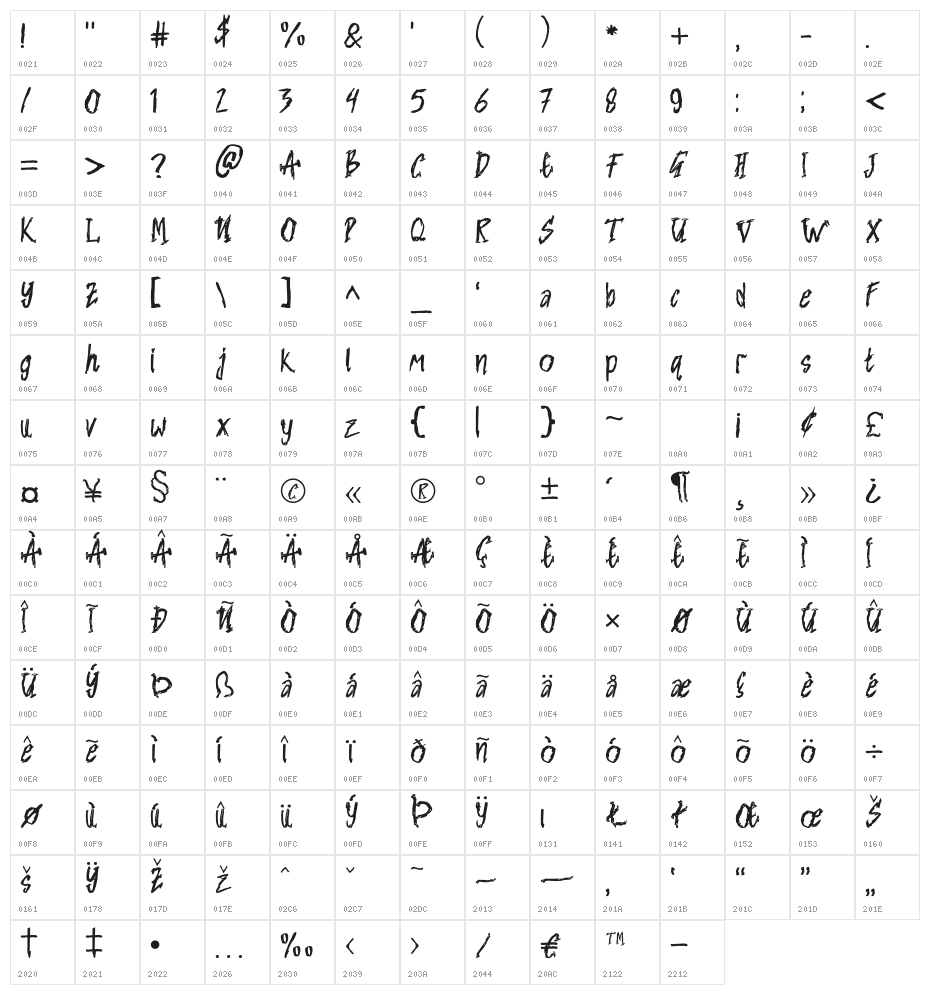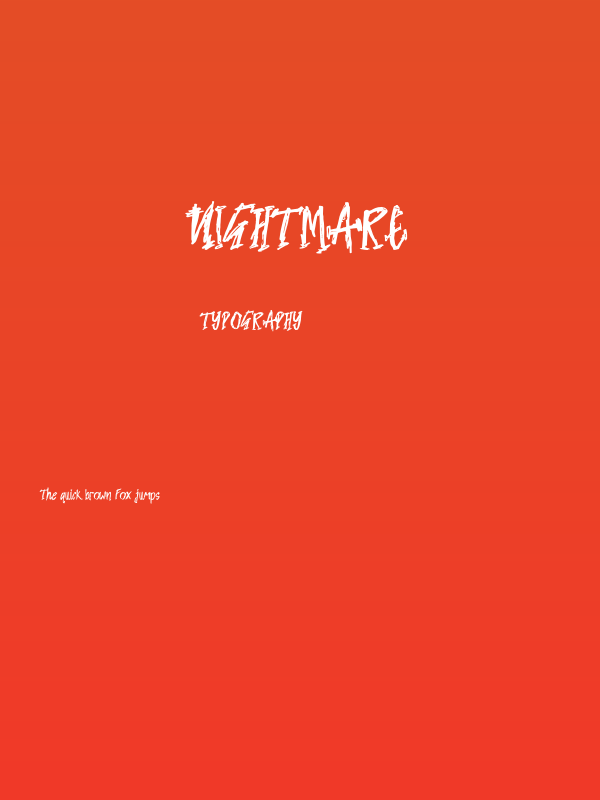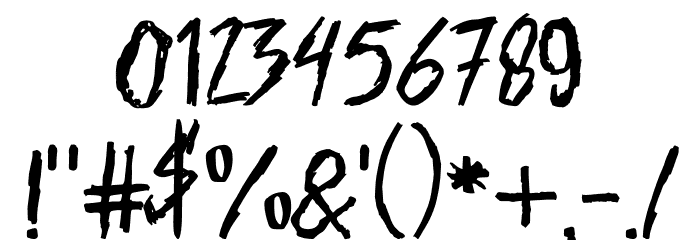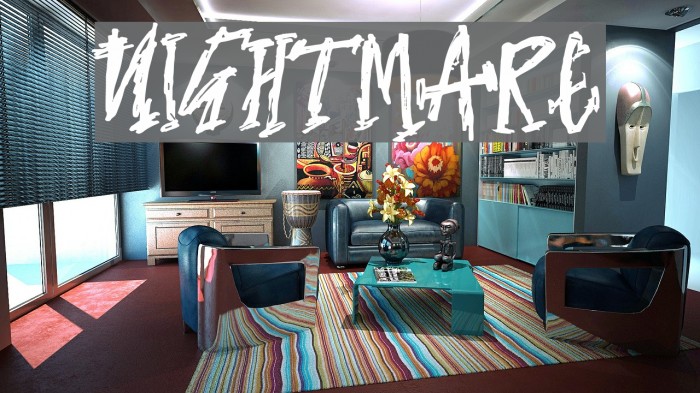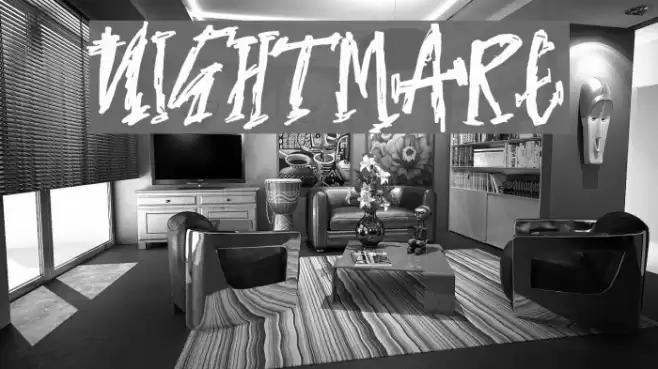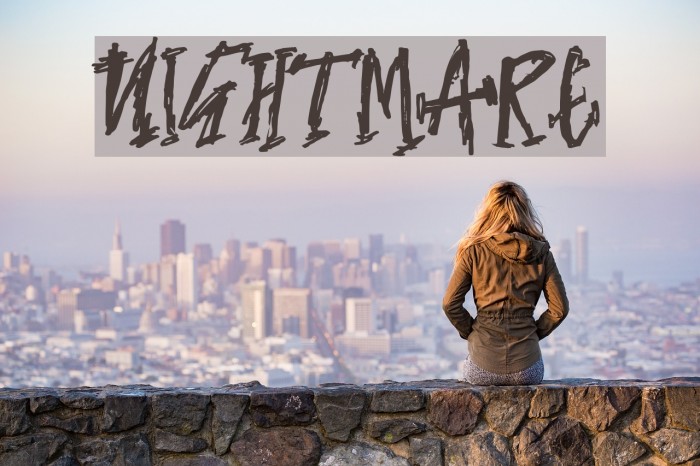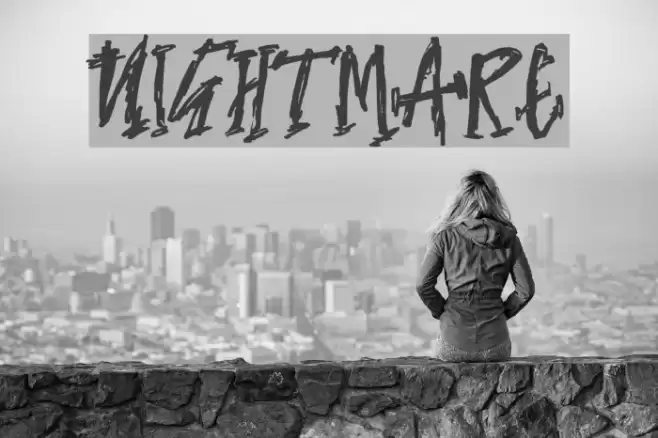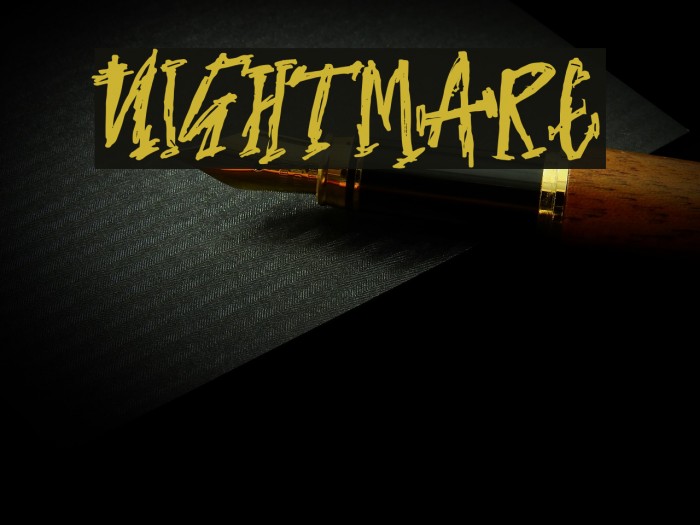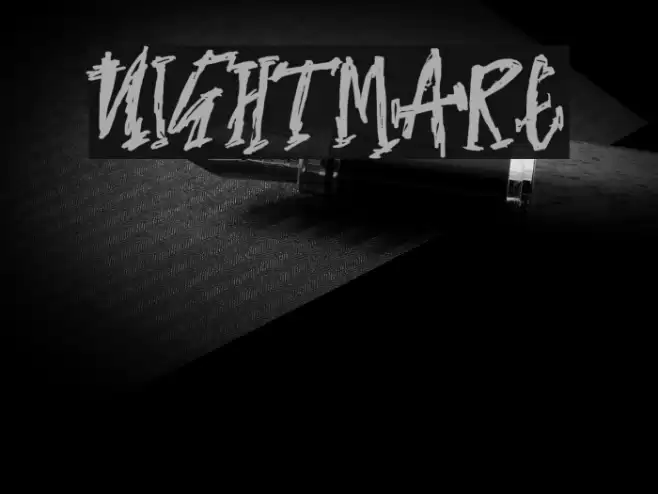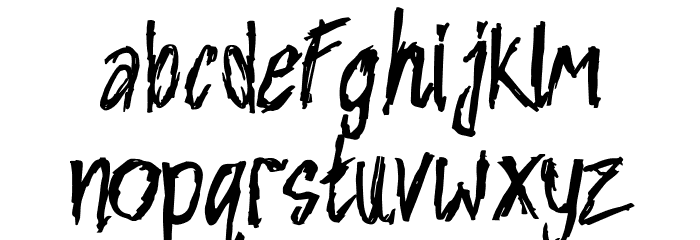
NIGHTMARE Font
✎ Horror
Randi Ilhamsyah
| Gesamtstil | Edgy, Chaotic, Distressed |
| Anwendungsfall | Headlines, Posters, Album Covers |
| Vorgeschlagene Projekte | Ideal for horror-themed posters, edgy album covers, rebellious branding, or grunge-style graphics. |